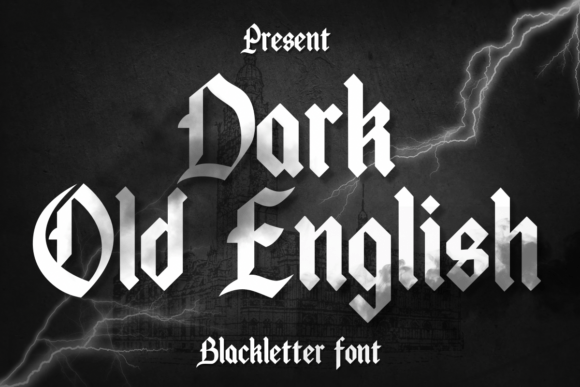
Dark Old English
適切なデザイン要素を見つけるのは難しい場合がありますが、Dark Old Englishは作品を即座に引き立てる優れたコレクションを提供します。
POD(オンデマンド印刷)製品、結婚式の招待状、またはソーシャルメディアのグラフィックを作成している場合でも、Dark Old Englishは理想的です。